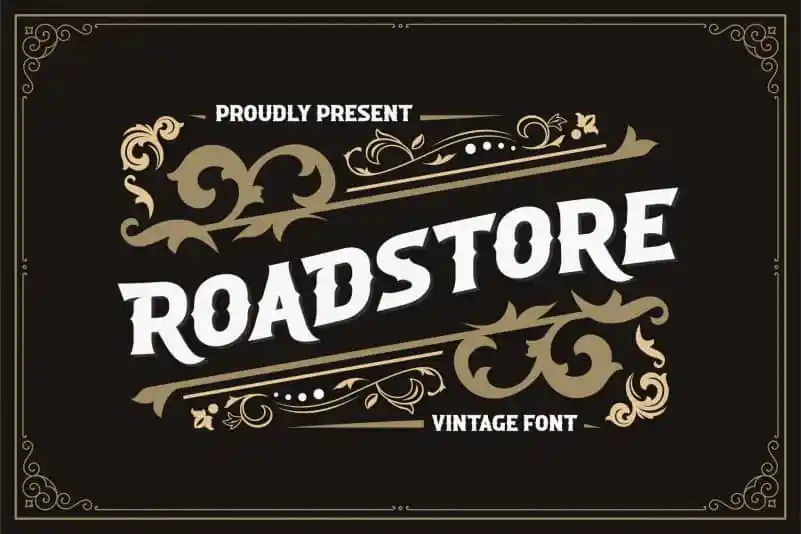
Roadstore Display Font – Download Grátis
A fonte Roadstore Display é uma criação única que combina elegância com um toque nostálgico e retro para criar uma sensação de viagem no tempo. Ideal tanto para logotipos quanto para texturas digitais, esta font vem da Almarkhatype, designer por trás do 99designs. Se você busca uma fonte vintage que dê ao seu design um toque diferenciado e interessante, esta é a escolha perfeita. Suas alternativas especiais e suporte multilinguagem garantem que seja versátil para qualquer projeto. Inspirada na movimentação de artes decorativas e arquitetura, ela promete enriquecer sua identidade visual com um toque único. Seja você uma empresa, designer gráfico ou criativo, esta fonte é certamente algo a considerar ao buscar personalizar seu trabalho para criar uma experiência mais memorável.